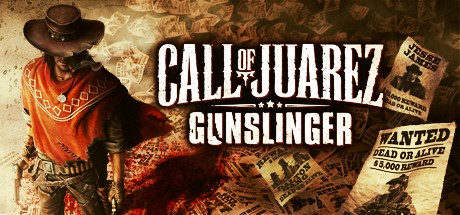
Suche diese Western-Style Schrift
Ich suche diese Schrift, oder etwas ähnliches. Was könnte das denn sein?
Hatte diese Schrift vergessen, also die Schrift von dem Text "Call of Juarez".